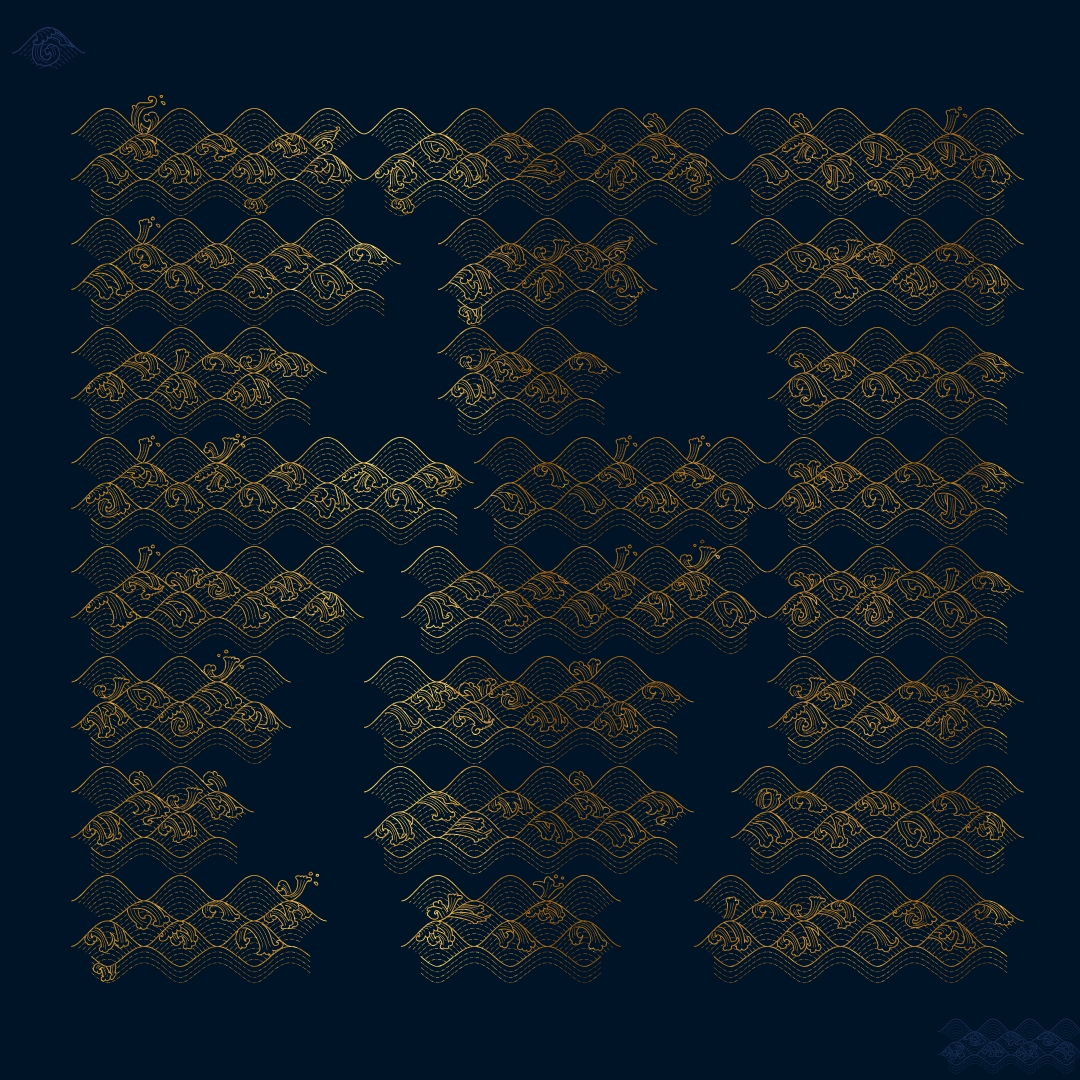
ฟอนต์ ฟอง
ฟอนต์ฟอง อักษรรูปฟองคลื่นน้ำลายไทย อ่านยาก ไฟล์ใหญ่ พิมพ์ได้บรรทัดเดียว
อย่าเอาไปพิมพ์ยาวๆแบบเน้!!
ชื่อฟอนต์ : ฟอง
ฟอนต์ฟอง อักษรรูปฟองคลื่นน้ำลายไทย อ่านยาก ไฟล์ใหญ่ พิมพ์ได้บรรทัดเดียว